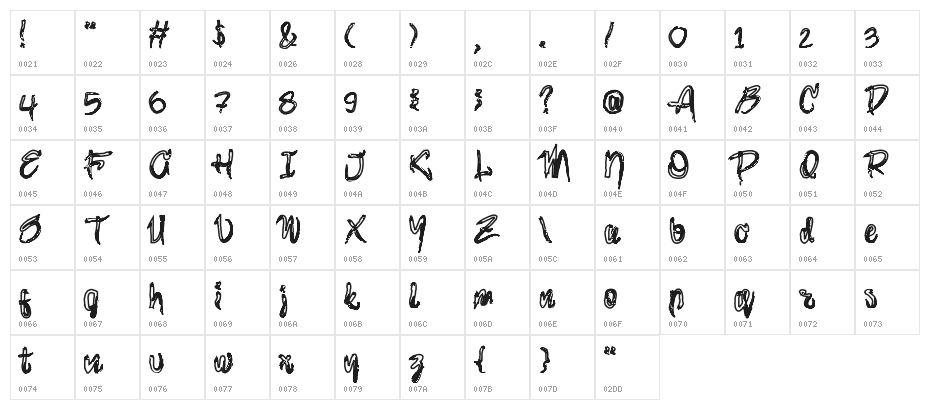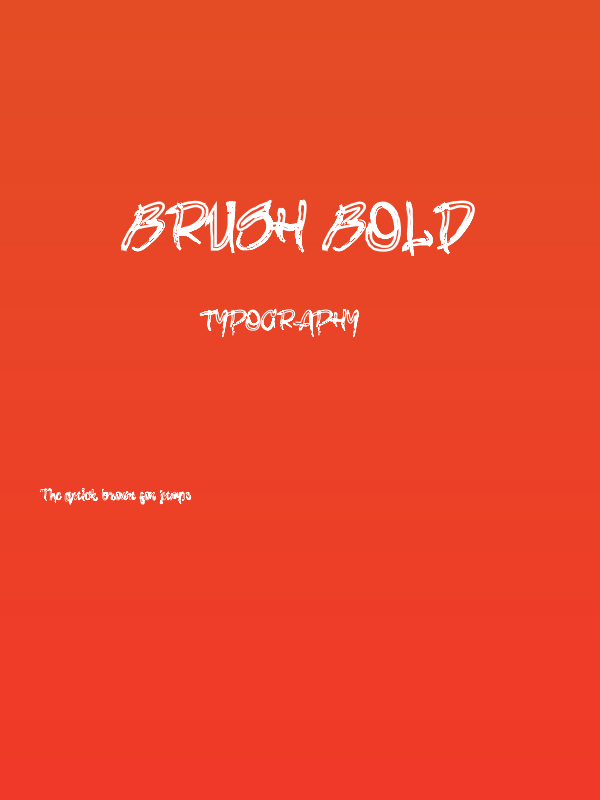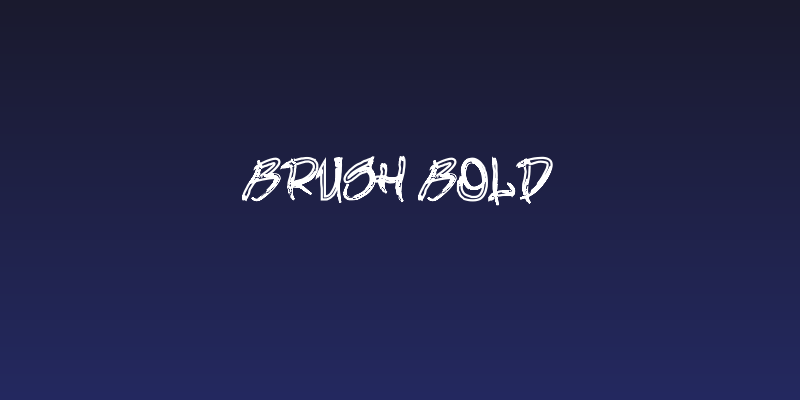
brush Bold Font
| Gesamtstil | Modern, Decorative |
| Vorgeschlagene Projekte | Ideal for creative projects such as posters, album covers, branding for artistic ventures, and any design that benefits from a bold, hand-crafted look. |